오늘은 디자인 작업이나 문서 작성에 활용할 수 있는 멋진 폰트들을 소개해드리려고 합니다. 폰트는 단순히 글자를 표현하는 도구가 아니라, 전체적인 분위기와 가독성에 큰 영향을 미치는 중요한 요소입니다. 다양한 스타일과 특징을 가진 폰트들을 잘 활용하면, 여러분의 작업물이 한층 더 돋보일 수 있습니다.
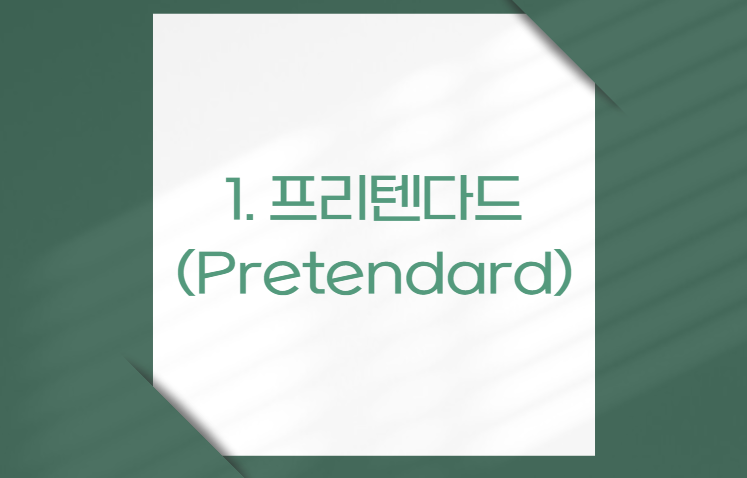
1. 프리텐다드 (Pretendard)
프리텐다드의 특징
프리텐다드는 최근 많은 디자이너들 사이에서 인기를 끌고 있는 폰트입니다. 이 폰트는 다음과 같은 특징을 가지고 있습니다:
- 다양한 굵기 지원: 프리텐다드는 얇은 글씨체부터 굵은 글씨체까지 다양한 굵기를 지원합니다. 이를 통해 제목, 본문, 강조 텍스트 등 다양한 용도로 활용할 수 있습니다.
- 뛰어난 가독성: 이 폰트는 글자의 모양이 깔끔하고 명확하여 긴 문장이나 단락을 읽을 때도 눈에 부담이 적습니다. 특히 작은 크기로 사용해도 가독성이 유지됩니다.
- 모던한 디자인: 프리텐다드는 현대적이고 세련된 느낌을 주는 디자인으로, 다양한 디자인 프로젝트에 잘 어울립니다.
프리텐다드 사용 예시
프리텐다드는 다양한 디자인 작업에서 활용될 수 있습니다. 몇 가지 예시를 들어보겠습니다:
- 웹 디자인: 프리텐다드는 웹사이트의 본문 텍스트나 제목에 사용하기 좋습니다. 특히 블로그나 뉴스 사이트에서 긴 글을 읽을 때 가독성이 뛰어나기 때문에 많이 사용됩니다.
- 인쇄물 디자인: 브로셔, 포스터, 명함 등 인쇄물에서도 프리텐다드는 그 매력을 발휘합니다. 다양한 굵기를 활용하여 시각적인 계층 구조를 쉽게 만들 수 있습니다.
- 앱 UI 디자인: 모바일 앱의 사용자 인터페이스에서도 프리텐다드는 훌륭한 선택입니다. 작은 화면에서도 글자가 명확하게 보이기 때문에 사용자 경험을 향상시킬 수 있습니다.
프리텐다드의 장점
프리텐다드를 사용하면 다음과 같은 장점을 누릴 수 있습니다:
- 일관성 있는 디자인: 다양한 굵기를 지원하기 때문에 하나의 폰트로 일관성 있는 디자인을 유지할 수 있습니다.
- 다양한 플랫폼에서의 호환성: 웹, 인쇄물, 모바일 등 다양한 플랫폼에서 잘 어울리며, 각 플랫폼의 특성에 맞게 최적화된 디자인을 제공합니다.
2. 나눔고딕
나눔고딕의 특징
나눔고딕은 네이버에서 개발한 폰트로, 한국어 웹 환경에서 많이 사용되는 대표적인 폰트 중 하나입니다. 이 폰트는 다음과 같은 특징을 가지고 있습니다:
- 친근하고 부드러운 느낌: 나눔고딕은 글자의 모서리가 둥글고 부드러워서 친근한 느낌을 줍니다. 이로 인해 사용자들이 편안하게 읽을 수 있습니다.
- 온라인 사용에 적합: 나눔고딕은 웹사이트와 같은 온라인 환경에서 최적화되어 있으며, 다양한 해상도에서도 선명하게 보입니다.
- 다양한 굵기와 스타일: 나눔고딕은 Regular, Bold, ExtraBold 등 다양한 굵기와 스타일을 제공하여, 제목과 본문 등 다양한 용도로 활용할 수 있습니다.
나눔고딕 사용 예시
나눔고딕은 다양한 온라인 및 오프라인 환경에서 활용될 수 있습니다. 몇 가지 예시를 들어보겠습니다:
- 블로그 포스팅: 나눔고딕은 블로그 포스팅의 본문 텍스트로 많이 사용됩니다. 가독성이 뛰어나고, 독자들에게 친근한 느낌을 주기 때문에 블로그 독자들이 글을 읽기 편합니다.
- 웹사이트 텍스트: 나눔고딕은 웹사이트의 본문 텍스트나 메뉴, 버튼 등 다양한 요소에 사용하기 좋습니다. 특히 정보 전달이 중요한 뉴스 사이트나 포털 사이트에서 많이 사용됩니다.
- 프레젠테이션 자료: 나눔고딕은 프레젠테이션 자료에서도 유용합니다. 깔끔하고 명확한 글자 모양 덕분에 청중들이 내용을 쉽게 이해할 수 있습니다.
나눔고딕의 장점
나눔고딕을 사용하면 다음과 같은 장점을 누릴 수 있습니다:
- 다양한 플랫폼에서의 호환성: 웹, 인쇄물, 프레젠테이션 등 다양한 플랫폼에서 잘 어울리며, 각 플랫폼의 특성에 맞게 최적화된 디자인을 제공합니다.
- 한국어 최적화: 나눔고딕은 한국어 텍스트에 최적화되어 있어, 한글을 사용하는 모든 환경에서 뛰어난 가독성을 제공합니다.
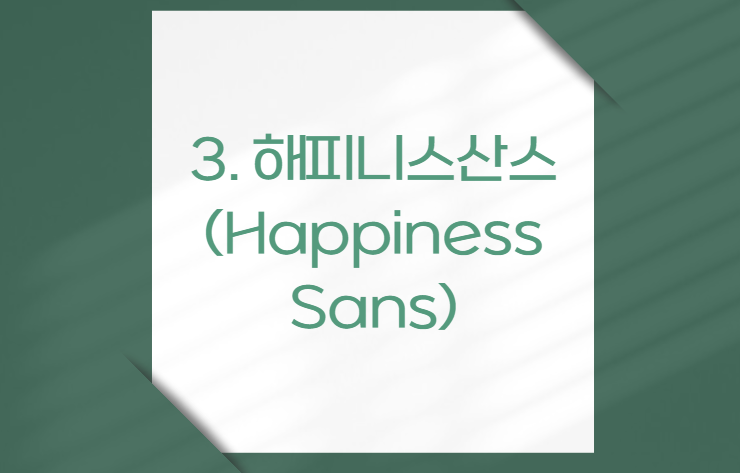
3. 해피니스산스 (Happiness Sans)
해피니스산스의 특징
해피니스산스는 현대백화점 전용 서체로 개발된 폰트로, 경쾌하고 깨끗한 느낌을 주는 것이 특징입니다. 이 폰트는 다음과 같은 특징을 가지고 있습니다:
- 경쾌하고 깨끗한 느낌: 해피니스산스는 글자의 모양이 깔끔하고 경쾌하여, 밝고 긍정적인 분위기를 연출할 수 있습니다.
- 현대백화점 전용 서체: 이 폰트는 현대백화점의 브랜드 아이덴티티를 강화하기 위해 개발되었으며, 브랜드의 고급스러움과 세련됨을 잘 표현합니다.
- 다양한 굵기와 스타일: 해피니스산스는 Regular, Bold 등 다양한 굵기와 스타일을 제공하여, 제목과 본문 등 다양한 용도로 활용할 수 있습니다.
해피니스산스 사용 예시
해피니스산스는 다양한 디자인 작업에서 활용될 수 있습니다. 몇 가지 예시를 들어보겠습니다:
- 광고 디자인: 해피니스산스는 광고 디자인에서 많이 사용됩니다. 경쾌하고 깨끗한 느낌 덕분에 제품이나 서비스의 이미지를 긍정적으로 전달할 수 있습니다.
- 브랜드 아이덴티티: 해피니스산스는 브랜드 아이덴티티를 강화하는 데 유용합니다. 특히 현대백화점과 같은 고급 브랜드에서 많이 사용됩니다.
- 포스터 및 배너 디자인: 해피니스산스는 포스터나 배너 디자인에서도 그 매력을 발휘합니다. 다양한 굵기를 활용하여 시각적인 계층 구조를 쉽게 만들 수 있습니다.
해피니스산스의 장점
해피니스산스를 사용하면 다음과 같은 장점을 누릴 수 있습니다:
- 일관성 있는 디자인: 다양한 굵기를 지원하기 때문에 하나의 폰트로 일관성 있는 디자인을 유지할 수 있습니다.
- 브랜드 이미지 강화: 해피니스산스는 브랜드의 고급스러움과 세련됨을 잘 표현하여, 브랜드 이미지를 강화하는 데 도움이 됩니다.
- 다양한 플랫폼에서의 호환성: 웹, 인쇄물, 광고 등 다양한 플랫폼에서 잘 어울리며, 각 플랫폼의 특성에 맞게 최적화된 디자인을 제공합니다.